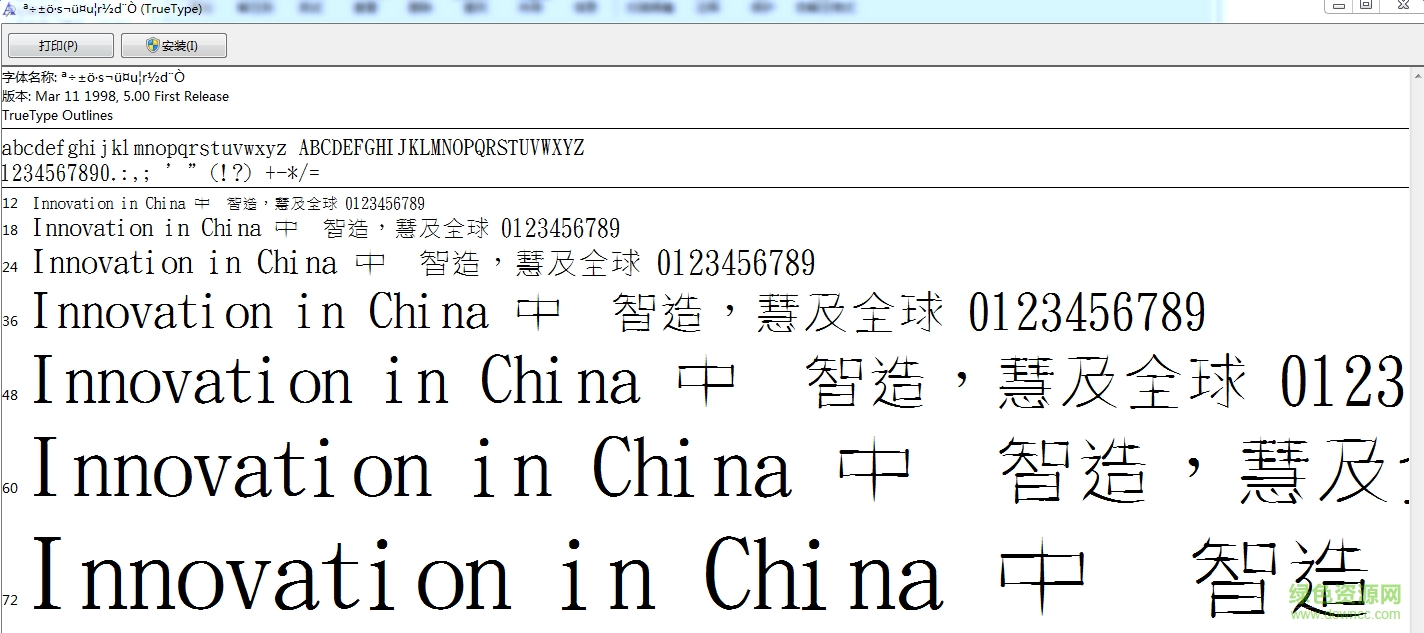
金梅新美工字范例字體是一款金梅類(lèi)美工字體軟件,金梅美工的字體給人非常好看的感覺(jué),深受廣大年輕人的喜愛(ài),還有更多好看字體盡情期待,歡迎到綠色資源網(wǎng)下載體驗(yàn)!
金梅新美工字范例是一款金梅類(lèi)美工字體,字體效果比較好看,喜歡美工體字的朋友可以下載使用看看效果如何。